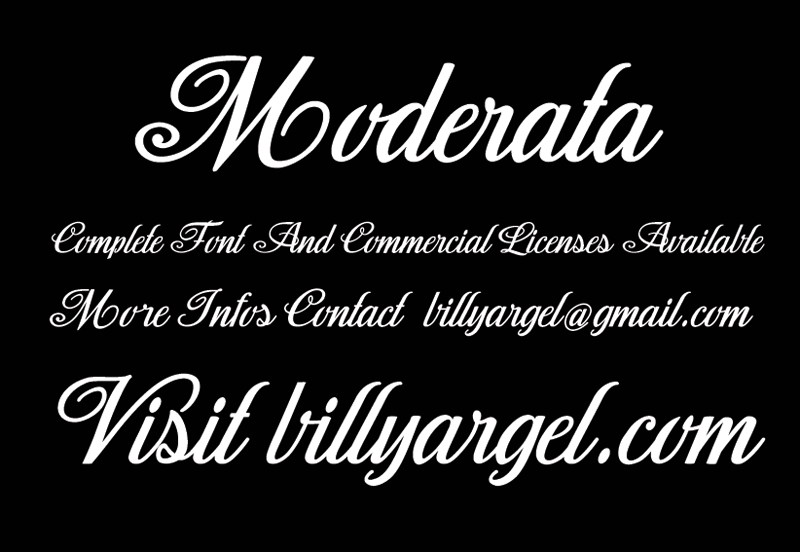
A fonte Moderata Script é uma elegante opção para quem busca uma mão lavrada e única no seu projeto. Ela foi criada pelo designer Billy Argel, conhecido pela sua habilidade de criar texturas meticulosamente detalhadas. Esta mão-dura se assemelha a escrita de alguém que tem um pouco mais de dificuldade na caligrafia, dando uma cara humana e única ao texto. Se você está procurando por fontes para projetos pessoais ou criações artísticas com personalidade, esta é uma ótima escolha. A fonte Moderata Script captura a essência de um estilo de escrita handwritten que transmite emoção e vivacidade. Ela pode ajudar em cartazes publicitários, designs de produtos, capas de livros ou qualquer outro projeto onde você precisa de uma personalização extra. Designer como Billy Argel tem a habilidade rara de criar algo que é tanto original quanto familiar, tornando sua fonte uma opção popular entre designers e artistas digitais. Se você está procurando por essa experiência de texto handwritten única, pode encontrá-la em nossa biblioteca de fontes online. Além disso, se o uso comercial for desejado, Billy Argel oferece facilidades para que isso possa ocorrer também. Por favor, visite a página da web do designer (www.billyargel.com) e site da fonte (http://www.facebook.com/billyargelfonts) para obter mais informações e contatar o criador. Você pode começar agora seu projeto com uma dose especial de personalidade através desta fonte handwritten única, feita sob medida para você.